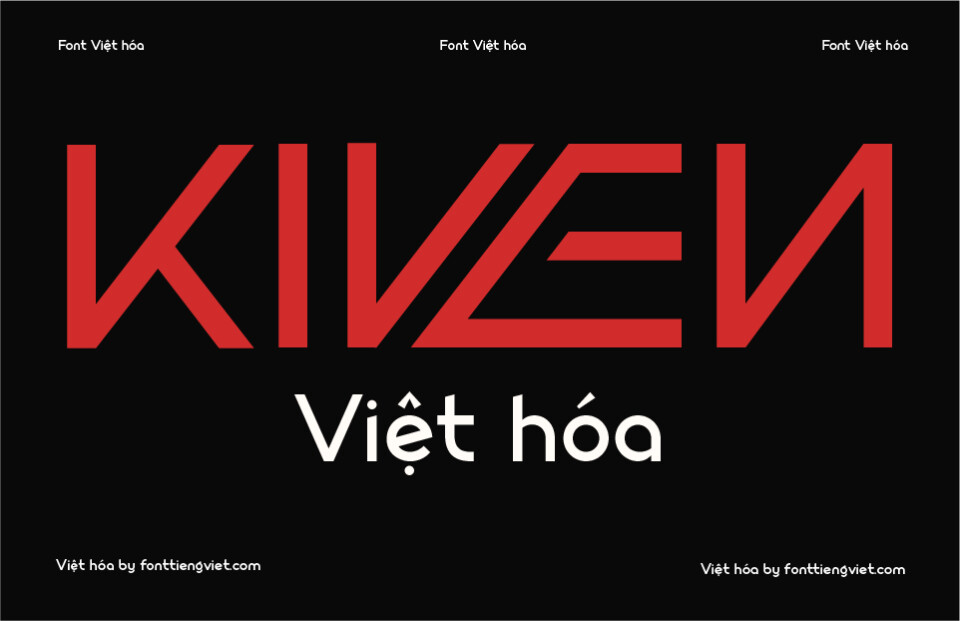
Font Việt hóa 1FTV VIP Kiven
Trong cộng đồng thiết kế đồ họa tại Việt Nam hiện nay, việc tìm kiếm một bộ Font Việt hóa 1FTV VIP Kiven chất lượng cao luôn là ưu tiên hàng đầu của các designer. Đây là một bộ font sở hữu đường nét tinh tế, hiện đại và cực kỳ linh hoạt, giúp các tác phẩm nghệ thuật trở nên sống động và thu hút hơn bao giờ hết. Khi sử dụng Font Miễn Phí, người dùng không chỉ tiết kiệm được chi phí mà còn có cơ hội trải nghiệm những phong cách chữ mới lạ, được tối ưu hóa hoàn toàn cho ngôn ngữ tiếng Việt với đầy đủ các dấu thanh chuẩn xác nhất. 1FTV VIP Kiven chính là sự lựa chọn hoàn hảo để nâng tầm thương hiệu và tạo điểm nhấn khác biệt cho mọi dự án sáng tạo từ cơ bản đến nâng cao.
Đặc điểm nổi bật của Font Việt hóa 1FTV VIP Kiven
Bộ Font Việt hóa 1FTV VIP Kiven được biết đến với cấu trúc hình khối chắc chắn nhưng không kém phần mềm mại, tạo cảm giác thân thiện và chuyên nghiệp ngay từ cái nhìn đầu tiên. Đặc điểm này giúp font chữ dễ dàng ứng dụng vào nhiều loại hình thiết kế khác nhau. Đội ngũ thực hiện Việt hóa đã tỉ mỉ điều chỉnh từng khoảng cách giữa các chữ cái, đảm bảo hiển thị mượt mà trên cả màn hình kỹ thuật số lẫn bản in truyền thống. Điều này cực kỳ quan trọng đối với các bạn học sinh, sinh viên khi làm báo cáo hoặc các nhà thiết kế đang xây dựng bộ nhận diện thương hiệu cho doanh nghiệp.
Ứng dụng đa dạng trong thực tế
Với phong cách thiết kế hiện đại, 1FTV VIP Kiven thường xuyên được sử dụng cho các tiêu đề lớn trên website, bìa sách, áp phích quảng cáo và cả trên các nền tảng mạng xã hội như Facebook hay Instagram. Nhờ vào sự cân bằng giữa các nét thanh và nét đậm, bộ font này mang lại khả năng đọc hiểu tốt ở nhiều kích thước khác nhau. Ngoài ra, tính năng hỗ trợ đầy đủ các ký tự đặc biệt của tiếng Việt giúp người dùng hoàn toàn yên tâm, không lo gặp phải lỗi hiển thị dấu – một vấn đề phổ biến khi sử dụng các font chữ nước ngoài chưa được chỉnh sửa phù hợp.
Lưu ý khi lựa chọn font cho dự án
Khi sử dụng bộ font này, bạn nên chú ý đến khoảng cách dòng (leading) và khoảng cách chữ (kerning) để tối ưu hóa trải nghiệm thị giác. Đối với các đoạn văn bản dài, hãy cân nhắc sử dụng kích thước chữ vừa phải để người xem không bị mỏi mắt. 1FTV VIP Kiven phát huy sức mạnh tốt nhất khi đóng vai trò là font chữ tiêu đề hoặc các câu trích dẫn mang tính nghệ thuật cao.
Tổng kết về giá trị của bộ Font Việt hóa 1FTV VIP Kiven
Có thể khẳng định rằng, việc sở hữu bộ Font Việt hóa 1FTV VIP Kiven trong thư viện tài nguyên sẽ giúp bạn tự tin hơn trong việc triển khai các ý tưởng sáng tạo. Đây không chỉ là một công cụ hỗ trợ mà còn là nguồn cảm hứng bất tận cho những ai yêu thích cái đẹp và sự chỉn chu trong từng con chữ. Hãy truy cập ngay vào trang web Font Miễn Phí, Font Việt Hóa, Font Việt hóa 1FTV VIP Kiven để tải về và bắt đầu hành trình thiết kế của mình ngay hôm nay. Hy vọng bộ font này sẽ mang lại cho bạn những kết quả ấn tượng và thành công rực rỡ trong mọi dự án thiết kế sắp tới.